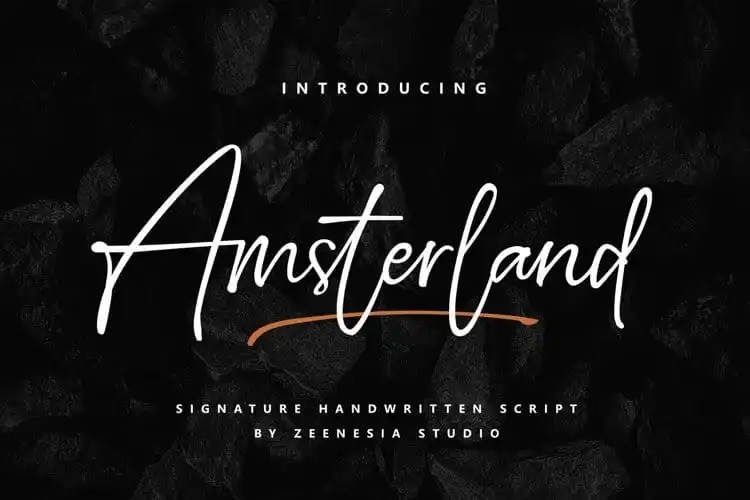
Amsterland Handwritten Font – Download Grátis
A Amsterland Handwritten é uma fonte escrita a mão única criada pelo designer Zeenesia Std, repleta de personalidade e encanto pessoal. Com traços curtos e rápidos que permitem uma rápida seca, ela também oferece um formato de exibição vintage, tornando-a perfeita para uso em design. Esta fonte é ideal tanto para aplicações formais quanto despretensiosas, transformando qualquer projeto em algo único e atraente. A Amsterland Handwritten atende ao seu objetivo criativo, sendo uma ótima escolha para um vasto leque de aplicativos como adesivos, rótulos, camisetas, cenários de cinema, posters, títulos de filme, anúncios e até mesmo logotipos. Seu charme não só torna a comunicação de seus desejos mais fácil, mas também adiciona um toque especial ao seu trabalho. Seja para uma cena cinematográfica memorável ou uma publicidade impactante no seu site, a Amsterland Handwritten fornecerá o acabamento perfeito à sua próxima criação. Este é um recurso gráfico que não apenas atende às suas necessidades de design visual, mas também encanta os olhos do consumidor.